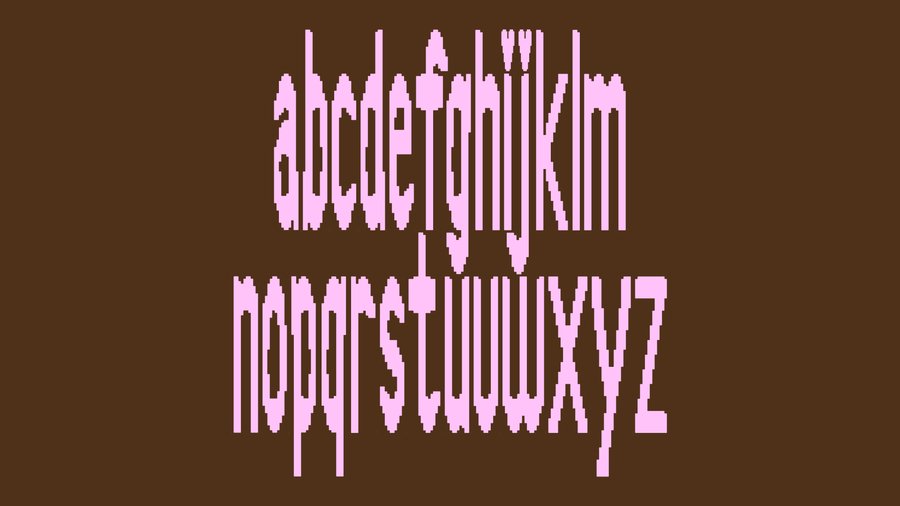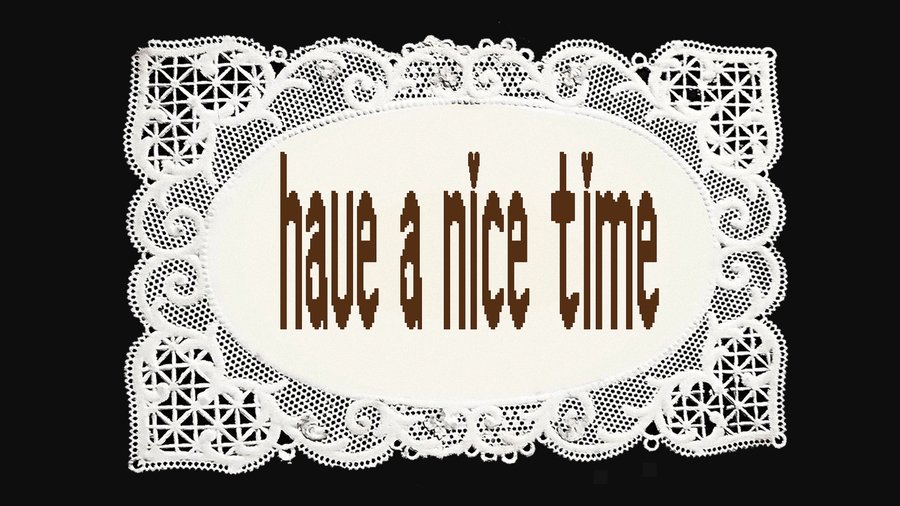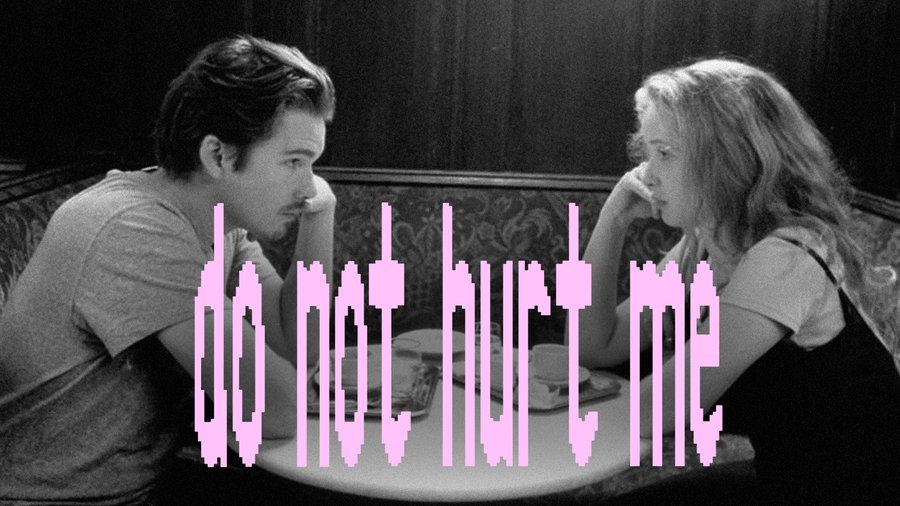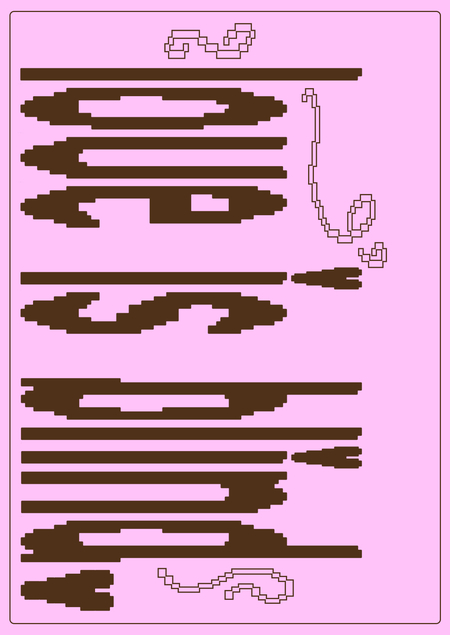
Love is blind. Акцидентный шрифт
Love is blind — акцидентный экспериментальный шрифт, исследующий границу между видимостью и пониманием. Шрифт построен на намеренном искажении привычной формы букв:
он сохраняет узнаваемость, но усложняет читаемость. Шрифт вдохновлён схемами для вышивания крестиком. Он обладает вертикальным ритмом и обратным контрастом.